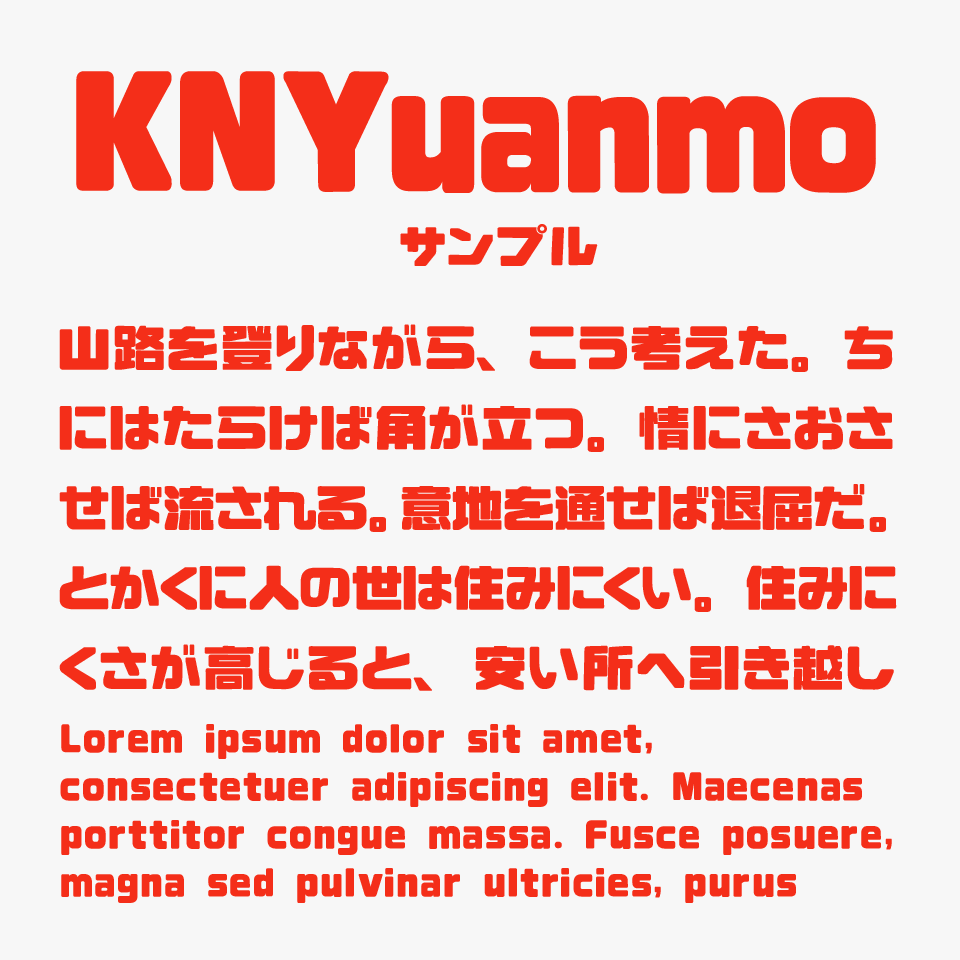
Kingnam Yuanmo(荆南缘默体)フォントは、力強くどっしりとした角張りのシルエットが印象的な日本語の仮名文字にも対応している中国語フォントです。
極太で、四角に押さまるように設計されている文字は、見た目の一見無骨ですが、丸みを帯びた角の処理によってどこか親しみやすさも感じるような仕上がりになっています。
中国語フォントのため、一部の漢字が日本文字と字形が異なる文字もあるので、ご注意ください。